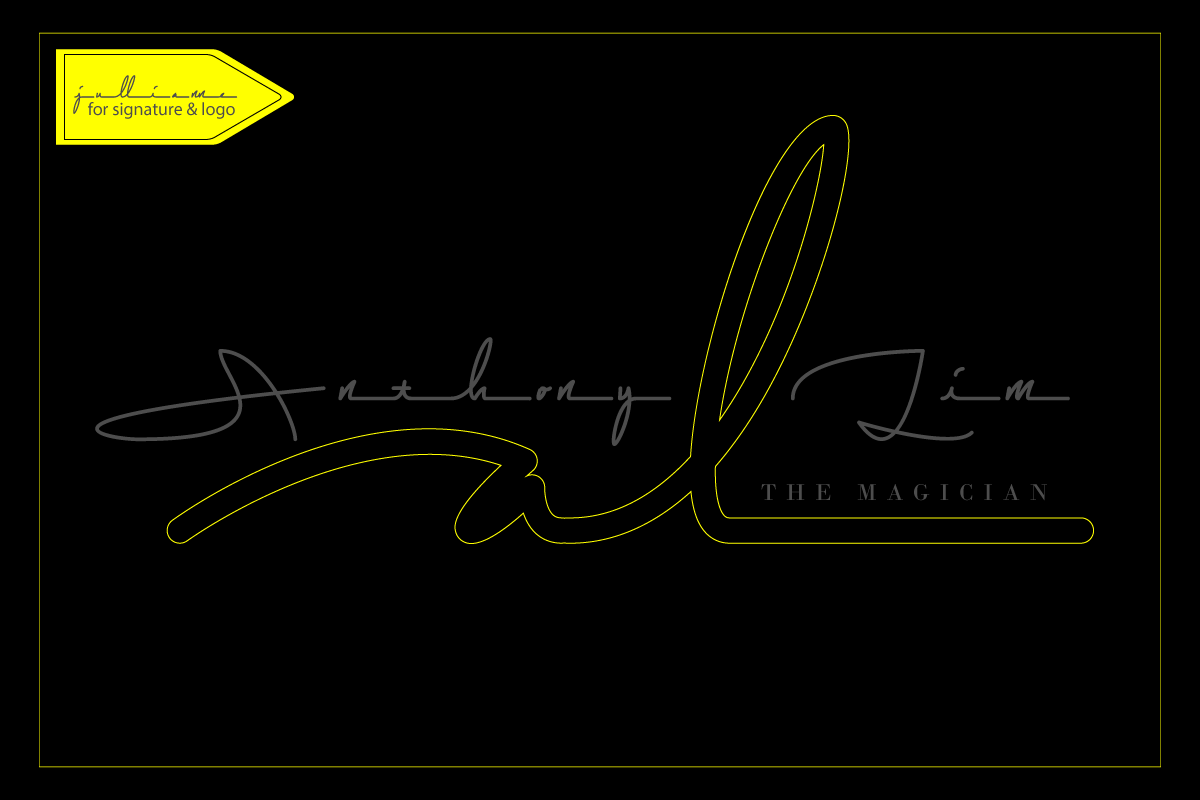
Jullian Nea是一款极具奢华和极简风格的脚本。这款收藏品完美地用于个人品牌,旨在使用商标和名片。Jullian Nea还可用于各种用途,如宣传、平面设计、印刷设计、网站设计、徽标、品牌,和其他。Jullian Nea是一款奢华且极简的字体脚本,没有任何线条风格。这款收藏品完美地用于个人品牌,旨在使用商标和名片。Jullian Nea还可用于各种用途,如婚礼宣传、平面设计、版画设计、网站设计、徽标、品牌等。